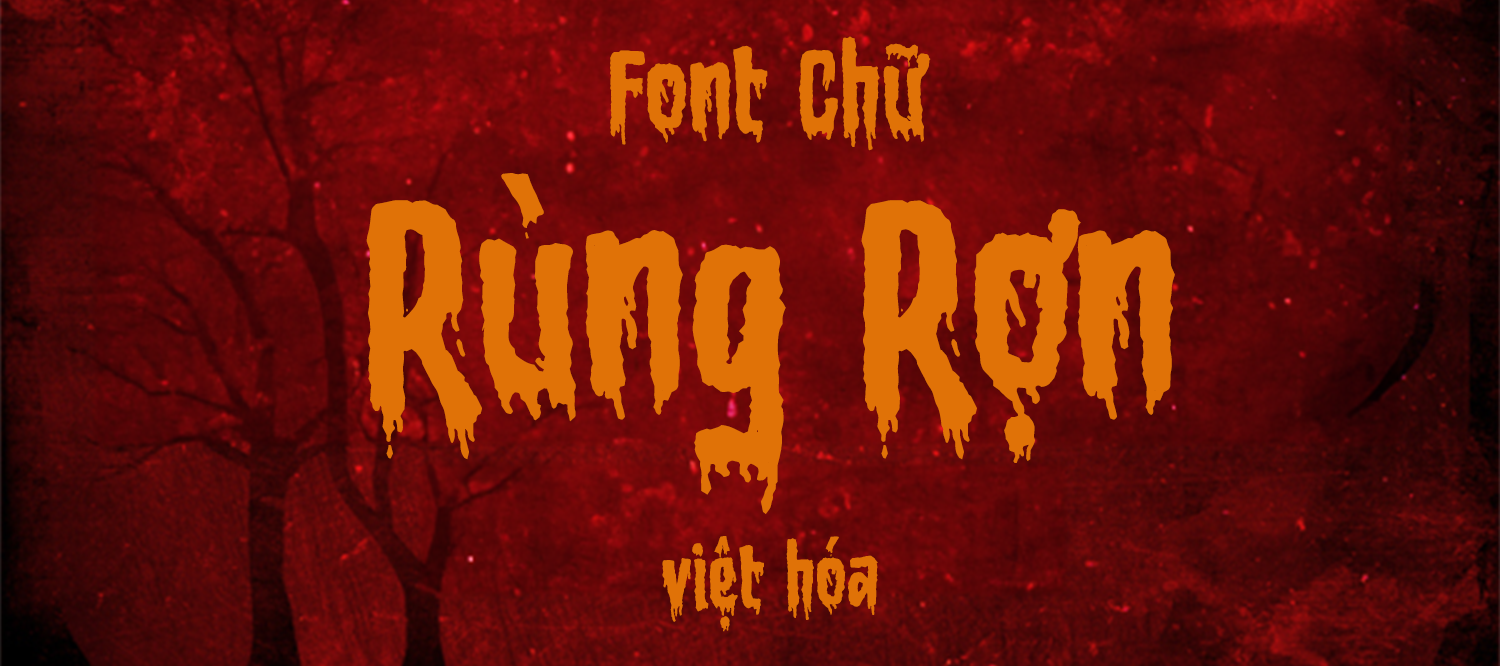
Font chữ không chỉ đơn thuần là một phương tiện truyền tải nội dung, mà còn là một yếu tố quan trọng giúp tạo nên cảm xúc và tâm trạng cho người xem. Trong các dịp đặc biệt như Halloween, thiết kế áp phích cho phim kinh dị, hoặc các sự kiện có tính chất u ám, rùng rợn, việc chọn lựa đúng font chữ có thể tạo ra hiệu ứng mạnh mẽ, làm tăng thêm sự kịch tính và thu hút sự chú ý của khán giả. Bài viết này sẽ giúp bạn hiểu rõ hơn về các font chữ rùng rợn, cách chúng được sử dụng và gợi ý một số font chữ phổ biến phù hợp với mục đích này.
Font chữ không chỉ truyền tải thông tin mà còn tạo ra cảm giác trực quan. Trong các thiết kế mang tính chất rùng rợn, sự lựa chọn font chữ đúng có thể mang lại cảm giác lo sợ, hồi hộp, và căng thẳng. Các font chữ rùng rợn thường có những đặc điểm sau:
Hình dáng góc cạnh, bất đối xứng: Những đường nét góc cạnh hoặc không đối xứng tạo nên sự bất thường, kích thích trí tưởng tượng và cảm giác bất an.
Nét chữ mờ nhòe, gãy khúc: Những font chữ có nét mờ, không liền lạc hoặc gãy khúc làm người xem liên tưởng đến sự u tối, hoang tàn.
Đường nét thô ráp: Các font chữ có đường nét thô ráp, không trau chuốt thường tạo nên cảm giác bạo lực, kinh dị.
Việc sử dụng font chữ rùng rợn trong thiết kế giúp người xem ngay lập tức nhận ra chủ đề và bầu không khí của sản phẩm, dù đó là một poster phim kinh dị, một banner quảng cáo cho lễ hội Halloween hay một bìa sách ma mị.
Dưới đây là một số font chữ rùng rợn phổ biến mà bạn có thể sử dụng cho thiết kế của mình:
1. TH Flavors Việt hóa: Một font chữ nổi tiếng với nét chữ giống như được lấy từ các bộ phim kinh dị cổ điển. TH Flavors Việt hóa có các đường nét dày, góc cạnh và tạo cảm giác bí ẩn, ghê rợn.
2. TH Bloody Camp Trial: Font chữ này có các đường nét giống như các vệt máu đang nhỏ xuống, tạo ra cảm giác khát máu và đầy hiểm ác.
3. SVN-Mukadua: Lấy cảm hứng từ bộ phim kinh dị cổ điển, font chữ này có các nét chữ thô ráp, gãy khúc, tạo cảm giác kinh hoàng, cổ xưa.
4. SVN-Endless Sorrow: Như tên gọi của nó, SVN-Endless Sorrow là một font chữ mô phỏng nét chữ của những xác sống, với những đường nét không đều và bất thường, mang lại cảm giác đe dọa, kinh dị.
5. TH Danger Night Font: Đây là một kiểu font cổ điển thường được sử dụng trong các tài liệu lịch sử châu Âu. Khi kết hợp với màu sắc tối, nó có thể tạo ra một cảm giác rùng rợn, huyền bí.
Khi sử dụng font chữ rùng rợn, bạn cần cân nhắc một số yếu tố để đảm bảo thiết kế của mình không chỉ hấp dẫn mà còn truyền tải đúng thông điệp:
Chọn màu sắc phù hợp: Font chữ rùng rợn thường phát huy tác dụng tốt nhất khi kết hợp với các màu tối như đen, đỏ, tím đậm hoặc xám. Những màu này giúp tăng cường hiệu ứng kinh dị của font chữ.
Không lạm dụng font chữ: Dù font chữ rùng rợn có thể rất ấn tượng, nhưng việc lạm dụng chúng sẽ làm giảm hiệu quả. Hãy sử dụng chúng một cách có chiến lược, chỉ ở những phần cần nhấn mạnh như tiêu đề hoặc những thông điệp quan trọng.
Kết hợp với hình ảnh: Để tạo ra một thiết kế hoàn chỉnh, hãy kết hợp font chữ với các hình ảnh hoặc biểu tượng liên quan đến chủ đề rùng rợn như ma quỷ, bóng tối, hoặc máu. Điều này sẽ giúp tạo nên một bức tranh tổng thể đầy ấn tượng.
Kiểm tra tính dễ đọc: Một trong những yếu tố quan trọng là tính dễ đọc. Dù font chữ có kinh dị đến đâu, nếu người xem không thể đọc được, thiết kế của bạn sẽ mất đi giá trị. Hãy chắc chắn rằng font chữ vẫn giữ được tính dễ đọc ở các kích thước khác nhau.
Nếu bạn muốn tạo ra một font chữ rùng rợn độc đáo cho riêng mình, dưới đây là một số bước cơ bản bạn có thể tham khảo:
Lấy cảm hứng: Xem qua các phim kinh dị, sách hoặc tranh vẽ về chủ đề này để lấy cảm hứng cho các nét chữ.
Sử dụng phần mềm thiết kế: Các phần mềm như Adobe Illustrator hoặc FontLab có thể giúp bạn tạo ra các nét chữ riêng biệt và tùy chỉnh chúng theo ý muốn.
Thử nghiệm: Sau khi tạo ra font chữ, hãy thử nghiệm nó trên các nền khác nhau và trong các kích cỡ khác nhau để đảm bảo tính hiệu quả và dễ đọc.
Font chữ rùng rợn không chỉ là một công cụ thiết kế mà còn là một yếu tố mạnh mẽ trong việc tạo ra bầu không khí cho sản phẩm của bạn. Bằng cách chọn lựa và sử dụng chúng một cách thông minh, bạn có thể tạo ra những thiết kế ấn tượng, gợi lên cảm giác kinh dị, hồi hộp và tạo dấu ấn sâu sắc trong lòng người xem.
Hãy thử nghiệm với các font chữ rùng rợn mà chúng tôi đã gợi ý, và khám phá cách chúng có thể biến đổi thiết kế của bạn theo cách mà bạn chưa từng nghĩ tới. Đừng ngại sáng tạo và kết hợp chúng với các yếu tố khác để tạo nên những tác phẩm nghệ thuật độc đáo và đầy sức hút.